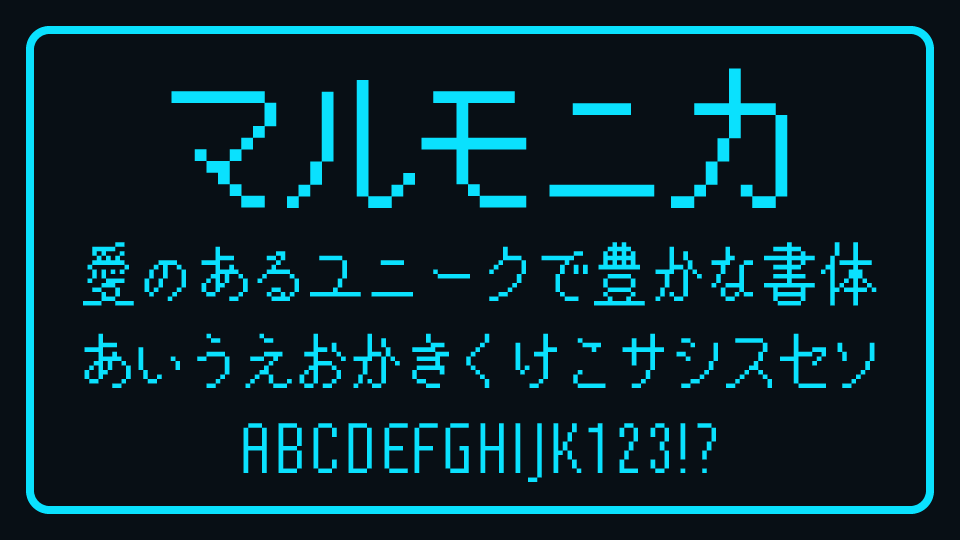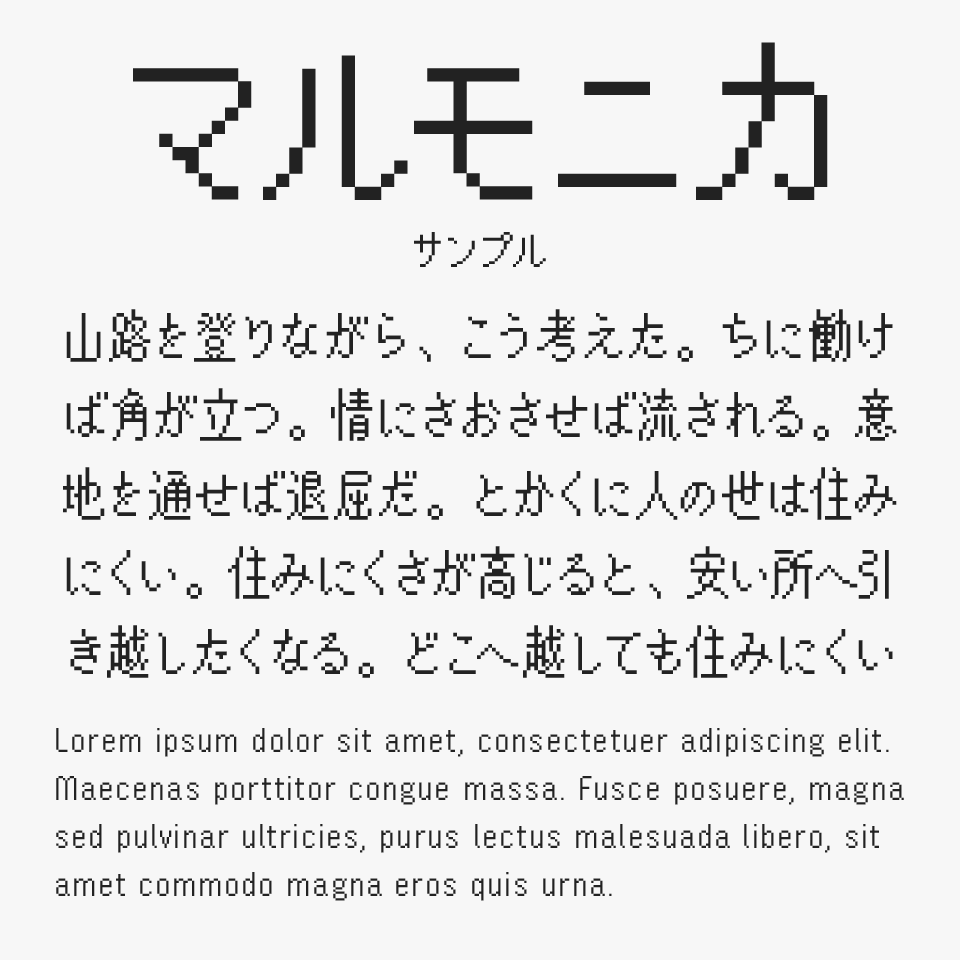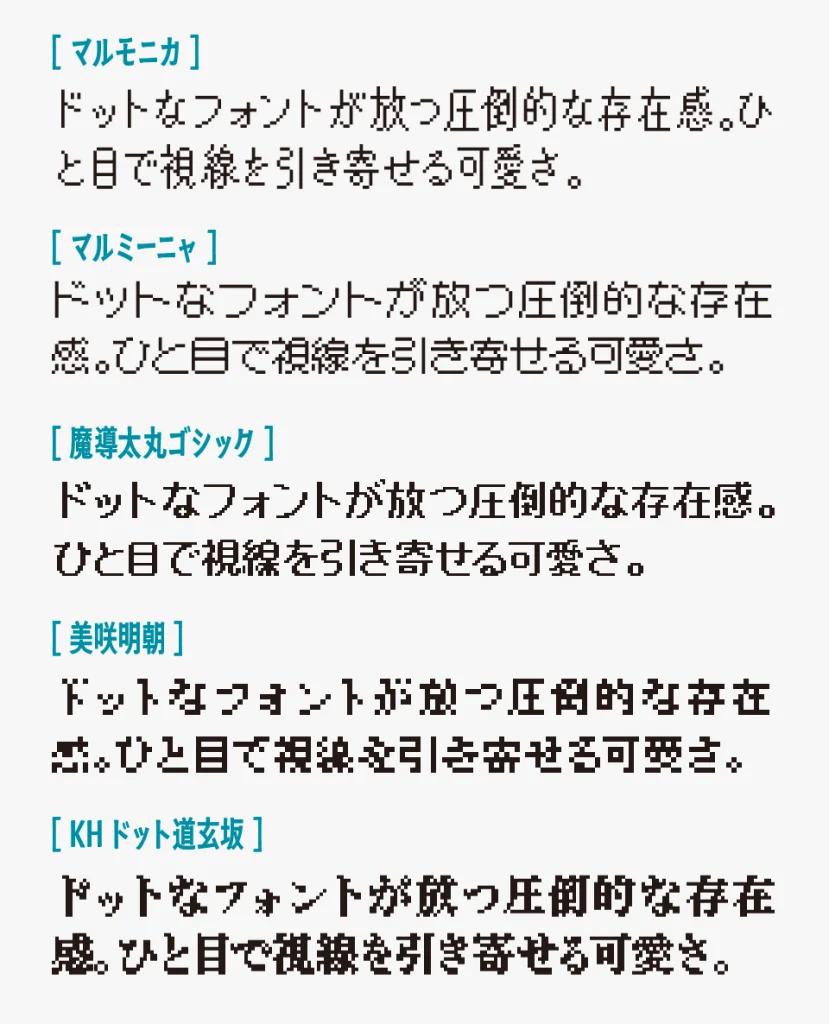
マルモニカ
マルモニカフォントは、「柔らかさ」と「シリアスさ」をあわせ持った独特な雰囲気が魅力のドットフォント・ピクセルフォントです。
ファミコンやゲームボーイ時代のゲーム画面を思わせるレトロな空気感がありながら、文字にはほんのり丸みが加えられているため、無機質になりすぎないやさしい印象があります。カクカクとしたピクセル感の中に、どこか可愛らしさや温かみを感じられるところも特徴のフォントです。
さらに、少し長体気味にデザインされていることで、昔ながらのドット文字らしさを残しつつも、現代的でスタイリッシュな雰囲気も感じられます。レトロゲーム風デザインはもちろん、Y2K・サブカル・MV・デジタル系ビジュアルなどにも相性が良く、“懐かしいのに新しい”空気感を楽しめるモダンなピクセルフォントです。
マルモニカを、ほかのドットフォントと比較してみると、スラッとした長体気味のシルエットと、ほんのり感じる可愛らしさが特に際立っています。
比較しているフォントは、「マルミーニャ」「魔導太丸ゴシック」「美咲明朝「KHドット道玄坂」もそれぞれのコンセプトがあるドットフォントなので、あわせて比較しながらチェックしてみてください。
マルモニカと、「マルミーニャ」「魔導太丸ゴシック」「美咲明朝」「KHドット道玄坂」を比較
収録文字は、ひらがな、カタカナ、漢字(JIS第1水準漢字2965字、第2水準漢字3390字)、アルファベット、記号まで収録されています。